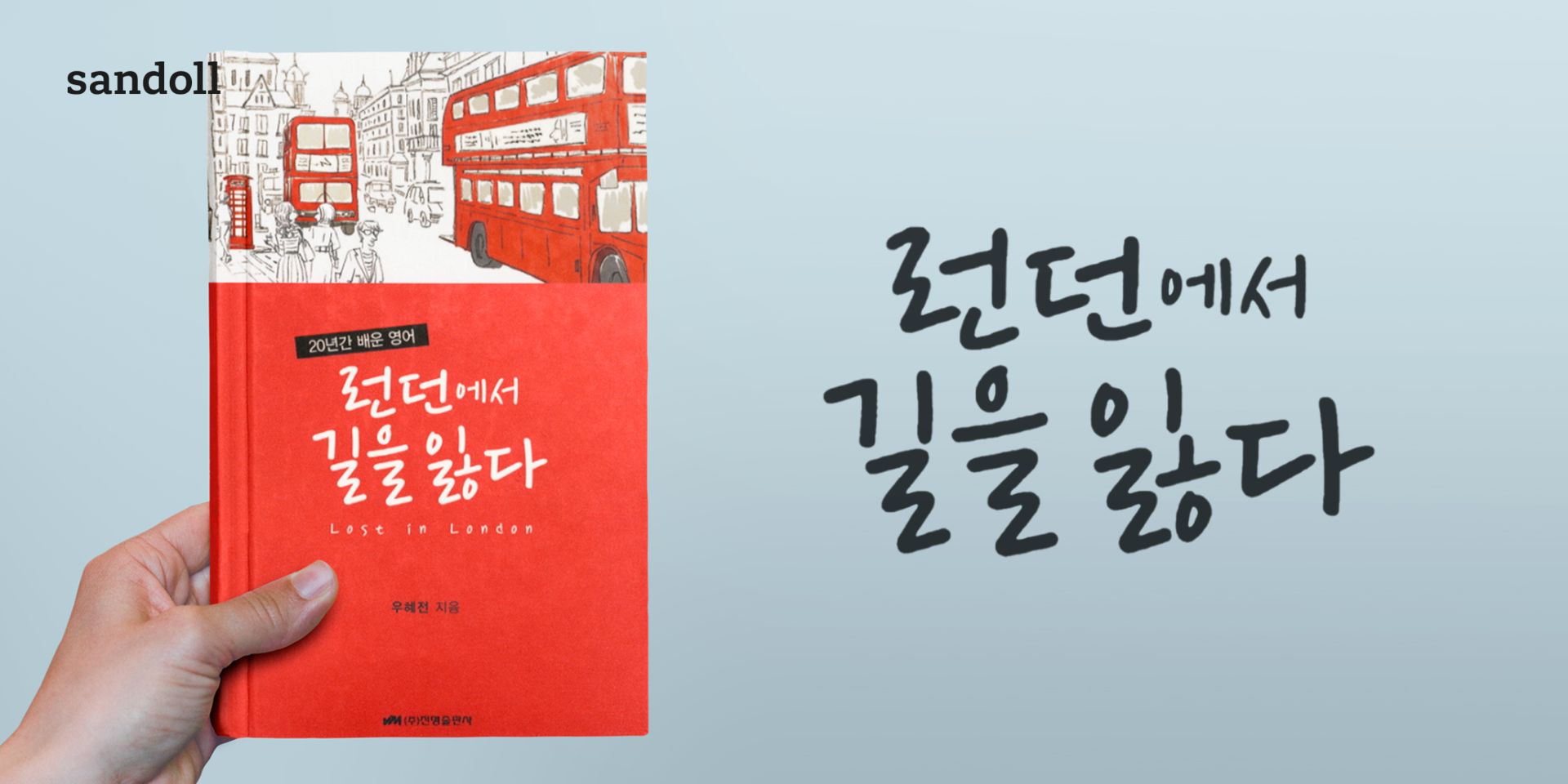
Sandoll 백종열펜
산돌 백종열펜은 백종열 감독이 네임펜으로 쓴 독특한 감성의 손글씨 폰트이다.영화와 CF로 유명한 백종열 감독이 직접 쓴 손글씨를 바탕으로 제작되었으며 색연필의 느낌(백종열필)과는 다르게 깔끔한 선처리의 네임펜으로 제작하여 차분한 느낌을 가지고 있다.